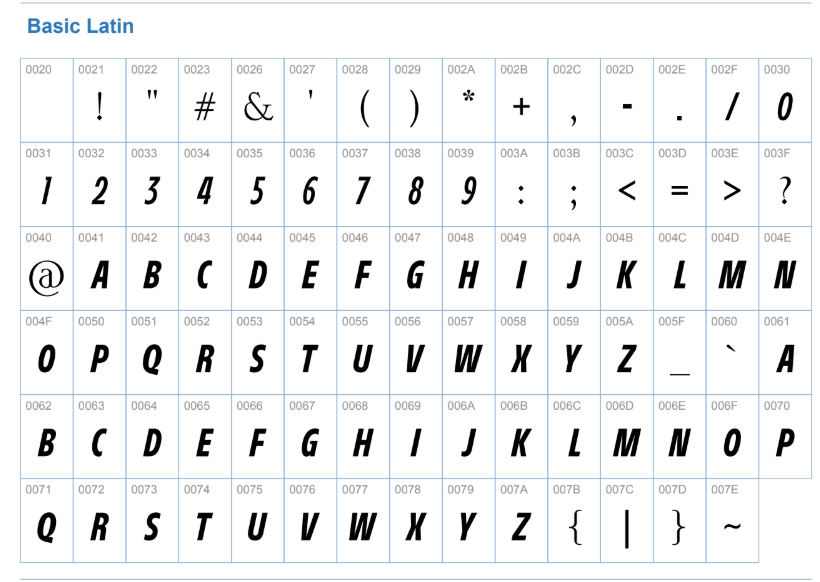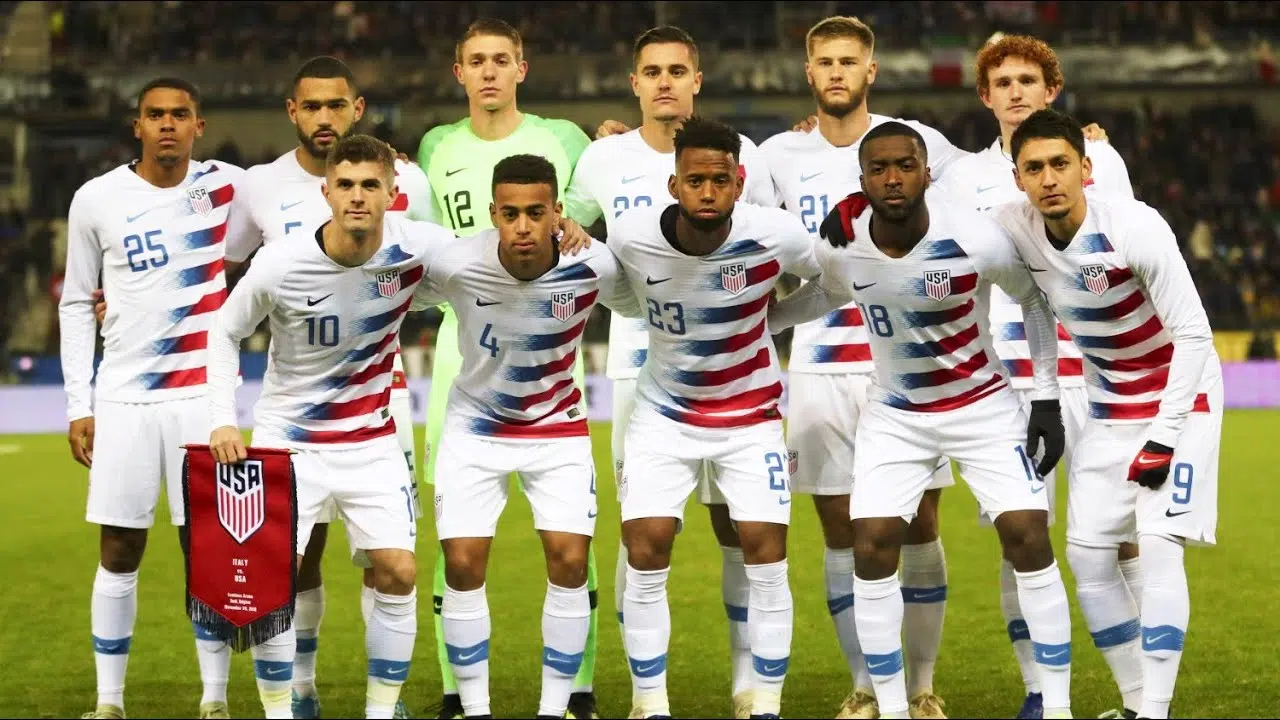
A contagem regressiva para a Copa do Mundo já começou, e a seleção dos Estados Unidos chega com identidade visual renovada para 2026. Entre os elementos que mais despertam a atenção de fãs e designers está a nova tipografia oficial, peça-chave do uniforme que será visto por milhões de pessoas nos estádios e nas transmissões.
A fonte carrega muito mais do que estética. Ela traduz a ambição do time anfitrião, mesclando tradição americana com um futebol cada vez mais enraizado no país. Quem trabalha com design esportivo ou quer customizar materiais com estilo profissional já está de olho nesse lançamento.
Estilo visual da tipografia
O design aposta em números com recorte dinâmico e hastes retas, criando um bloco visual firme. Pequenas serifas internas dão um toque de modernidade, enquanto o equilíbrio entre espessura e respiro garante leitura rápida mesmo a longa distância.
Na TV e nas fotos de campo, cada algarismo aparece limpo e bem definido, sem ruídos visuais que atrapalhem a identificação do jogador.
Aplicação no uniforme
No uniforme home, predominantemente branco, a fonte aparece em azul marinho com acabamento que remete a velocidade. O modelo away, em tom escuro, traz os números vazados em branco, garantindo contraste alto.
Já a terceira camisa, com grafismos inspirados na bandeira, recebe a tipografia em vermelho sólido, fechando o conjunto com personalidade.